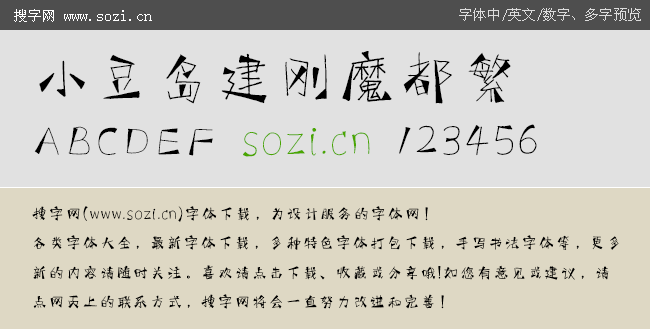
小豆島建剛魔都繁
搜字網(wǎng)提供一款小豆島小豆島建剛魔都繁中文字體下載,小豆島小豆島建剛魔都體是一款風(fēng)格偏硬的藝術(shù)字體。字形夸張變形,趣味十足。適合應(yīng)用于海報(bào)設(shè)計(jì)、POP設(shè)計(jì)、兒童產(chǎn)品包裝設(shè)計(jì)等應(yīng)用。